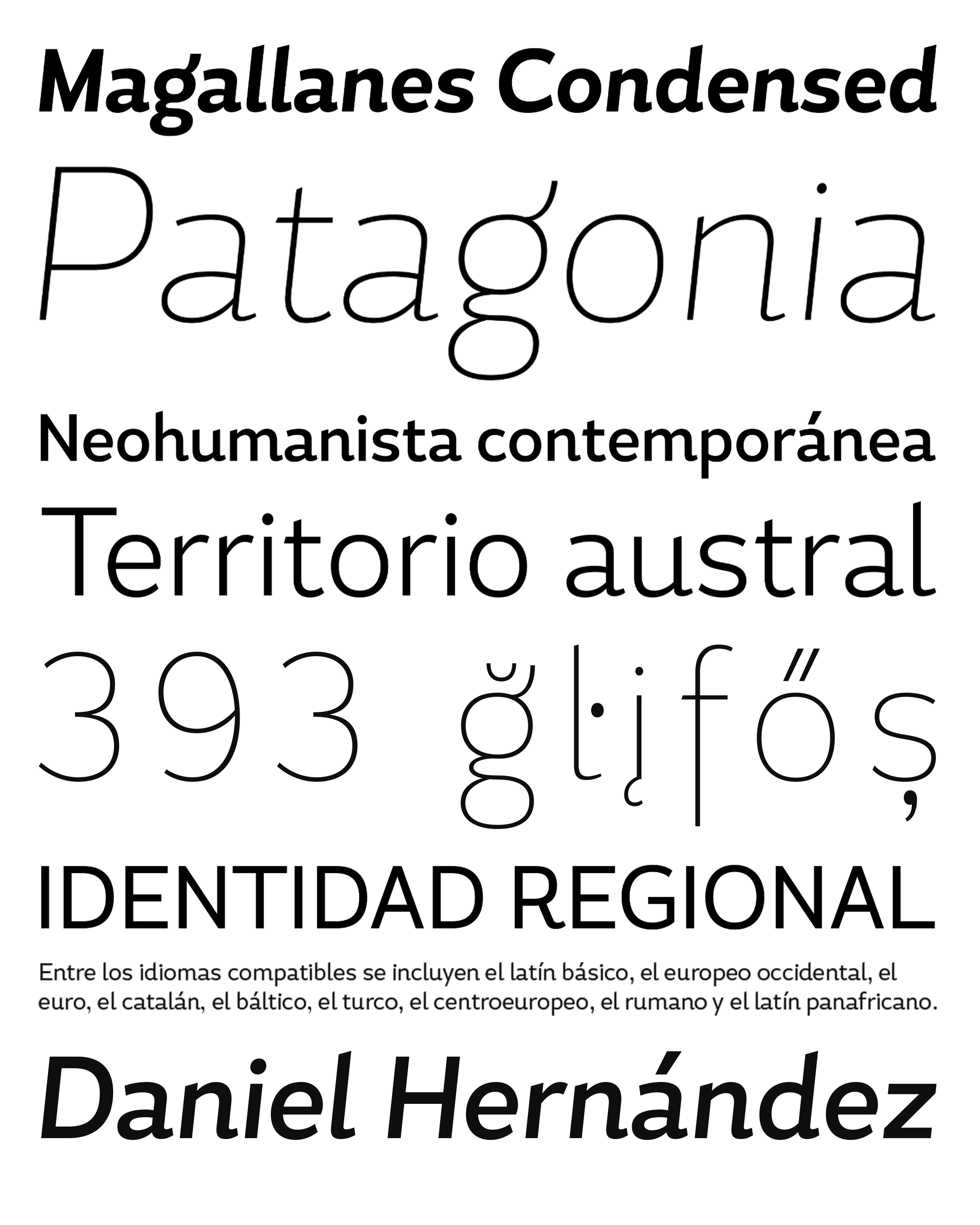
| Año | 2013 |
| Créditos | Daniel Hernández |
| Descripción | Salude a la nueva familia Magallanes Condensed, una fuente sin gracias neohumanista contemporánea diseñada por Daniel Hernández. Sus trazos y terminales están relacionados con los trazos caligráficos de las tipografías humanistas. Viene con 8 estilos, desde Ultra Light hasta Black, cada uno con su cursiva verdadera. Cada peso viene con glifos alternativos para un uso más dinámico. Magallanes es la fuente de titulación perfecta para complementar caras de texto en revistas, logotipos, etc. Entre los idiomas compatibles se incluyen el latín básico, el europeo occidental, el euro, el catalán, el báltico, el turco, el centroeuropeo, el rumano y el latín panafricano. |